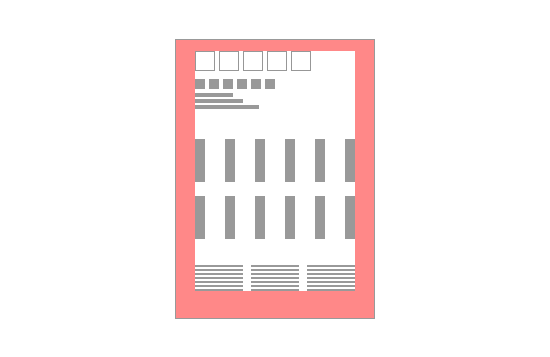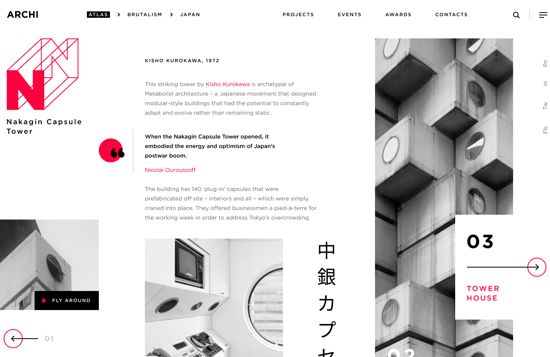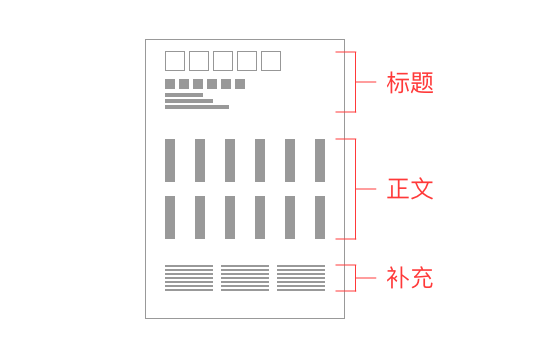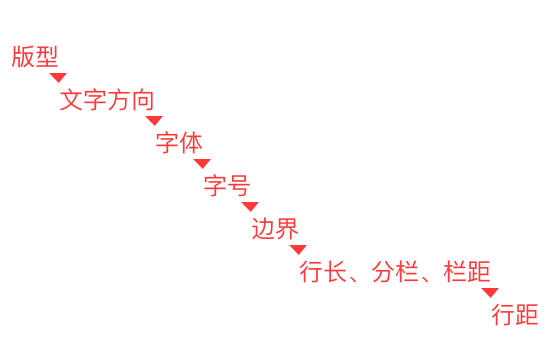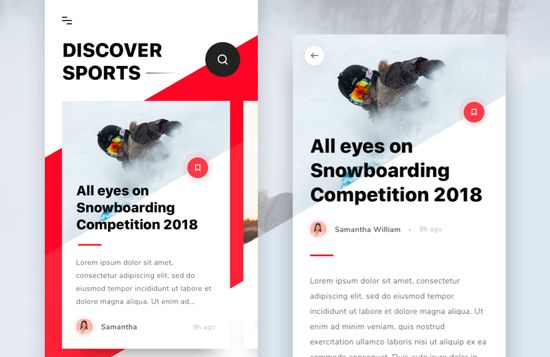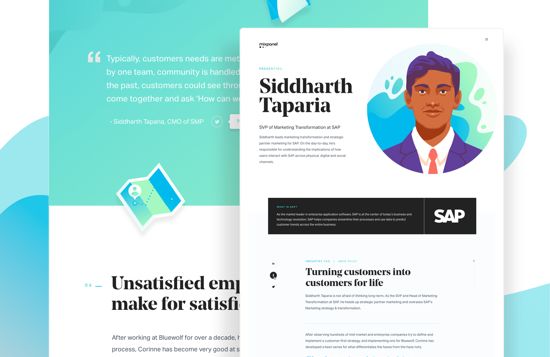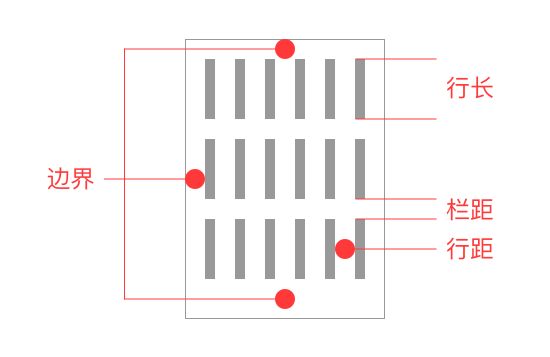
文字设计原理(三):文字的易读性
字体,只要不是特殊装饰性的文字,都不至于发生无法阅读的状况。字体的设计人员都预先做了某种程度的设定,但是这种设定只能是达到“可以阅读”。
在设计作品过程中,若要求达到“容易阅读”的文字组合,字体和字号的选择、文字和文字的间隔、行和行的间隔、字号的变化,都得依据版面来设计。
那究竟怎么样才算是“容易阅读”的文字编排呢?
“容易阅读”包含两个要素:“容易看”和“容易理解”。
“容易看”,是指阅读文字的时候遇到的障碍少。字号过小、行间距过窄、颜色刺眼等等,这些对阅读者来说都是障碍。要减少这些障碍,我们就必须要了解如何去配置易读的文字。
“容易理解”,是指我们在看到文字的一瞬间,就能理解大概其内容。我们站在读者的角度去考虑版面的设计,考虑如何去引导读者视线的顺畅移动,寻求用文字进行沟通交流的能力。
首先,我们根据设计对象去理解版面,有一个大致的版型构建在我们的脑海中。根据版型去决定文字的组合方向,是横排还是竖排更合适这个设计。
接下来,配合文章的氛围选择适合的“字体”,决定文字的“字号”。到了这个阶段,也就可以设定出“版心”,也就是页面上空白的部分。
最后,设定一行文字的“行长”,段落之间间隔的“栏距”,行之间间隔的“行距”,以及文字之间的“字距”。这些都是细微的部分,也是我们使文字更容易理解的必经过程。
通过以上这些步骤,我们大概就能理清,要设计一个容易阅读的文字版面,需要做的事情。接下来,让我们逐一来解决它们。
容易阅读的字号,会根据文字的目的、作用、读者对象而改变。
文字大略可以区分成标题部分、正文部分以及补充说明部分。
标题部分必然是版面中最显眼的地方,尤其是大标题,文字的尺寸必须比其它文字大且具有强调性。在大标题之外,还有诱导视线的“小标题”、补充内容的“副标题”、以内概述部分的“前言”。这些字号都要求比正文的大。
正文部分的文字量最多,也是阅读的核心部分。正文部分的字体大小也决定了整个版面的易读性。
在印刷物中,我们推荐正文为9pt的字号;
在web设计中,1920px分辨率下,12px的字号为最小字号;
而在移动端设计中,小字一般为20px。
当然,以上都不是规定必须得这样设定,只是在经验的总结下得出的结论。
“边界”也就是我们所理解的左右留白,这些留白不仅能帮助阅读,也会影响页面传达出的印象。
设定边界的目的,一方面为了防止页面元素在边界上导致的不完整呈现;
另外一方面,也是来自设计上的观点,为了防止在视觉上因为边界上的元素导致不整齐。
在印刷物中,我们要保证最少有5毫米左右的留白;
在web设计中,考虑到自适应,页面元素基本都在居中的750px里面;
而在移动端设计中,不同的产品有不同的风格,基本上有24px、40px的边界留白。
留白是影响页面印象的最主要的元素,根据不同的需求去做相应合适的处理。
为了让长篇的文章更容易阅读,在正文部分必须设定合适的行长与分栏。
在确定好字号和页边距之后,一行可以容纳多少个字符也相应确定了。如果只是简单的排成最多字数,那样就会因为一行过长而难以阅读。这个时候就必须要分“区块”,也就是“栏”。
在阅读的时候,我们的视线从一行的开头部分到另外一行的开头部分逐行移动,如果单行过长,可能视线就会弄错,导致阅读障碍。
如果是印刷物,每一行35毫米~55毫米左右的长度会比较容易阅读;
在web设计中,栏目可以根据页面栅格化去设定;
而在移动端,因为屏幕较小,可以不做考虑。
行距的大小,是为了让人感受到文章的“间距”的重点。
行距的确定要素很多,需要根据横排还是竖排、字号、字体、行长而去整体考虑设定。
正文部分的行距,一般设定为正文的半个字到一个字左右的尺寸。
字间距可以制造出阅读文章的韵律感。
不同的字体有不同的默认字间距的的设定,同一套字体里面,不同字的字间距也不同,以外文来说,“W”和“I”的字间距相差很大。如果不是有特殊的要求,一般对某套字体的字间距不做调整。
如果字间距设定很狭窄时,会呈现出密度感和张力;
如果希望有舒适悠然的感觉,可以尝试让字间距看起来宽松些。
随着视线自然流动来配置版面,就会让文字变得容易阅读。
我们在阅读的时候,都会无意识的按照某种顺序来浏览。图片和插图首先吸引了注意力,其次才开始阅读文字。
版面的文字以横排为主时,视线从左上到右下移动;
竖排时,视线从右上到左下移动。
整体文字部分来说,标题部分必须突出;
正文部分分栏排列,并且视线的折返应该是有规律的。
依照视线的流畅移动而形成的版面配置,是很标准的容易阅读的配置。有时候也可以突破标准,营造出欢乐气氛的方式。
给文字加点适度的变化,整个版面就能显现出强弱节奏,也更易读。
通过对照和比较来对元素进行差异化的表达,从而将差异的部分强调出来。
想要让文字有对比效果:
第一,改变文字本身设定的方法,如长、宽、字体以及色彩等,只要将一部分加以变化,就会和其它文字产生对比。
第二,改变文字的组合方法,如改变留白的空间、加上横线、改变行长和对齐方式等。
加上适度的对比,可以使文章的文字间出现强弱对比。强弱变化可使阅读文章时有韵律感,避免让读者觉得无聊。
以上部分都是如何让文字更易读,那有哪些是需要在设计的时候避免的呢?
这些不能做的约束,称为“禁忌”,也就是设计规范了。
如:在一行的开头不能出现句号、逗号、冒号等等标点符号;
同样,在一行结束的地方不能放置前引号、前括号等等;
同时,也不能将公司名称、产品名称之类的固有名词拆开。
最后,官方的提一句,文字的设定没有固有的规律,不是说你必须如何如何,只是你需要在充分理解这些规范的情况下,结合具体的设计需求,去做相应的调整,这才叫文字设计。